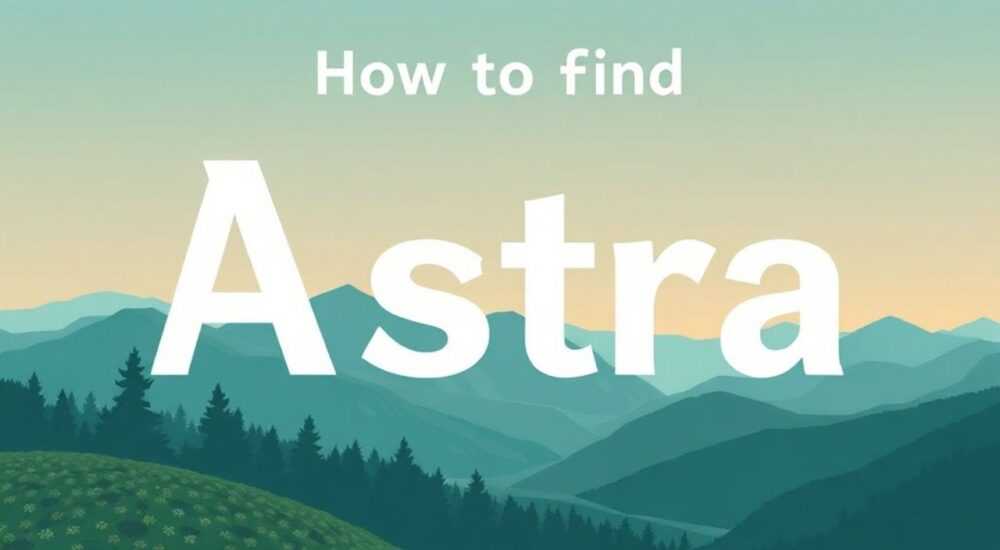
Как найти шрифт астра
В современном дизайне и верстке сайтов часто возникает необходимость найти конкретный шрифт, особенно когда речь идет о популярных решениях вроде Астра. Этот шрифт получил широкое распространение благодаря своей универсальности и четкости отображения на различных устройствах. Однако не все знают, как правильно определить и использовать этот типографический элемент в своих проектах.
Что такое шрифт Астра и почему его сложно найти
Шрифт Астра представляет собой уникальное семейство гарнитур, разработанное специально для улучшения читаемости текста на экранах. Интересно, что существует несколько вариаций этого шрифта: оригинальная версия, адаптированные варианты для веб-дизайна и модифицированные версии с дополнительными символами. Именно это многообразие часто становится причиной путаницы при поиске нужного варианта.
Основные сложности при поиске шрифта Астра:
- Наличие множества похожих шрифтов с похожими названиями
- Отсутствие единого репозитория или базы данных
- Сложность отличия оригинальной версии от копий
Для тех, кто занимается веб-разработкой или дизайн-проектами, важно точно определить, какой именно вариант шрифта требуется. В противном случае можно столкнуться с проблемами совместимости или юридическими последствиями из-за нарушения авторских прав.
Пошаговый алгоритм поиска шрифта Астра
Существует несколько проверенных методов для точной идентификации шрифта Астра. Первый шаг — анализ характеристик шрифта:
Характеристика |
Описание |
Как проверить |
Толщина линий |
Средняя толщина основных штрихов |
Увеличить изображение до 200% |
Пропорции букв |
Соотношение высоты к ширине |
Сравнить с референсным образцом |
Засечки |
Наличие и форма завершений штрихов |
Использовать графический редактор |
После предварительного анализа можно переходить к активным действиям:
- Используйте специализированные сервисы вроде WhatTheFont или FontSquirrel Matcherator
- Создайте скриншот с примером текста и загрузите его на платформу
- Проанализируйте предложенные варианты и сравните их с оригиналом
Альтернативные методы поиска и их особенности
Кроме автоматических сервисов существуют и другие способы найти шрифт Астра. Многие профессионалы предпочитают комбинировать различные подходы для повышения точности результата. Рассмотрим основные альтернативы:
Метод сравнения с эталонными образцами:
- Создание собственной базы данных шрифтов
- Использование каталогов печатных изданий
- Обращение к профессиональным типографам
Программные решения:
- Adobe Fonts с функцией автоматического распознавания
- FontBase с коллекцией открытых шрифтов
- Google Fonts API для интеграции в проекты
Примечательно, что каждый метод имеет свои преимущества и ограничения. Например, программные решения отлично подходят для быстрого поиска, но могут давать неточные результаты при работе со сложными гарнитурами. В то же время ручные методы более надежны, но требуют значительно больше времени.
Экспертное мнение: рекомендации от практиков
Алексей Кузнецов, ведущий дизайнер студии «Типографика Плюс», эксперт с 15-летним опытом создания корпоративных стилей:
«За годы работы с различными шрифтами я выработал несколько важных принципов. Во-первых, всегда начинайте с базового анализа характеристик шрифта. Это поможет сразу отсеять явно неподходящие варианты. Во-вторых, используйте комбинированный подход: автоматические сервисы плюс ручной анализ.»
Из личного опыта могу отметить интересный случай. Один клиент предоставил макет с шрифтом, который казался очень похожим на Астру, но имел несколько характерных отличий. После детального анализа выяснилось, что это была модифицированная версия шрифта, созданная для специфических целей. Пришлось создавать собственный вариант, максимально приближенный к оригиналу, но с учетом современных требований.
Частые вопросы и практические ответы
- Как отличить оригинальную версию Астры от подделок?
Проверьте наличие сертификата подлинности и сверьте ключевые характеристики с официальным описанием. Особое внимание уделите пропорциям букв ‘g’, ‘y’ и ‘Q’.
- Можно ли использовать найденный шрифт в коммерческих целях?
Необходимо обязательно проверить лицензионные условия. Некоторые версии доступны только для личного использования.
- Что делать, если автоматические сервисы дают неверный результат?
Попробуйте обратиться к профессиональным типографам или использовать несколько разных сервисов одновременно.
Перспективы развития технологий распознавания шрифтов
Современные технологии машинного обучения открывают новые возможности для точной идентификации шрифтов. Искусственный интеллект научился распознавать не только стандартные гарнитуры, но и их модификации, учитывая даже самые мелкие детали.
Например, новая технология DeepFont использует нейросети для анализа более 200 параметров шрифта одновременно. Это позволяет достигать точности распознавания до 98% даже при работе с искаженными или неполными образцами. Специалисты прогнозируют, что в ближайшие годы такие системы станут стандартом в типографической индустрии.